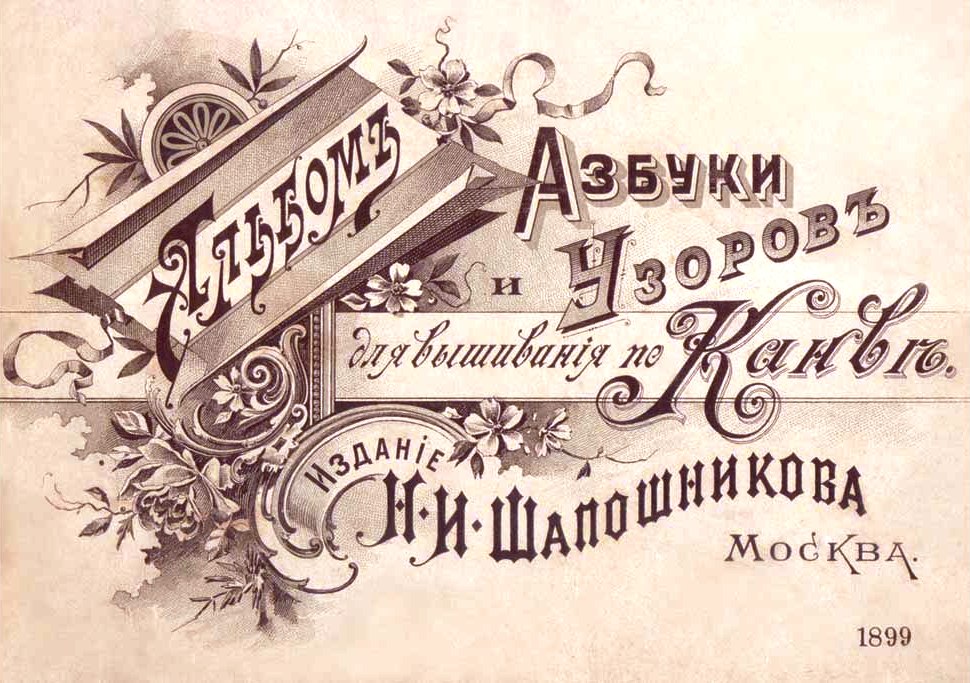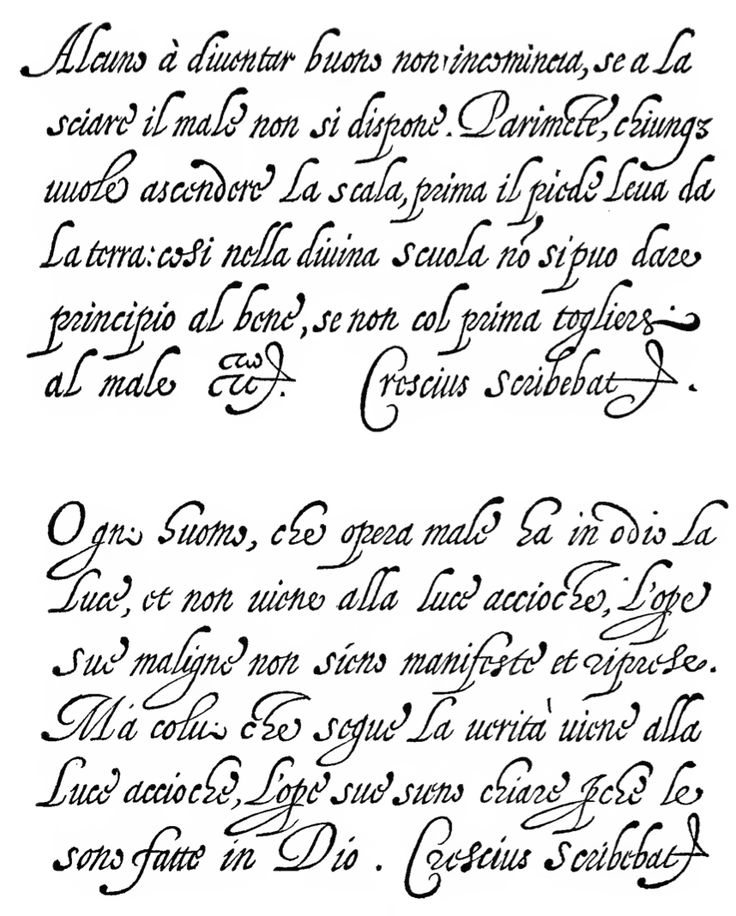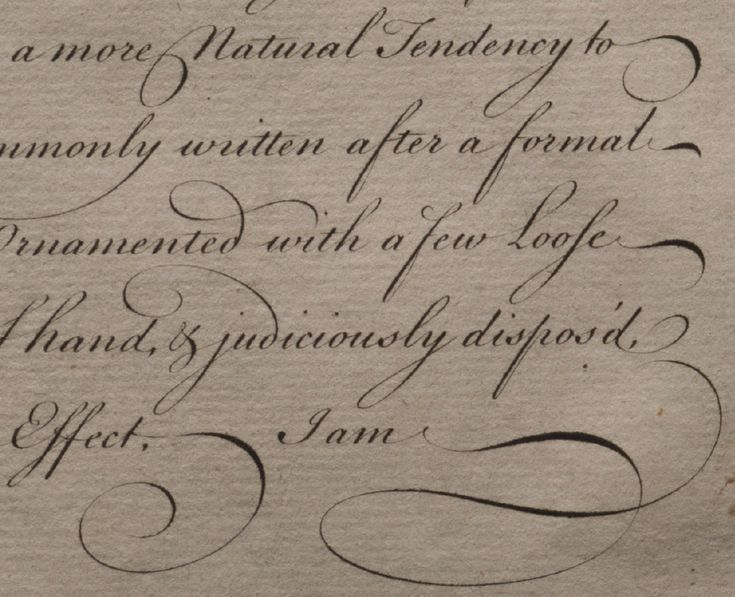
Лучшие шрифты для вашего сайта
Дизайн сайта проходит в много этапов. Один из последних, но также очень важных вопросов — это выбор шрифтов для оформления ваших текстов. У вас уже есть готовый дизайн сайта, планируете его наполнение, есть ли у вас готовые тексты и описания (копия) и графический дизайн? Итак, самое время начать работать над типографикой и выбирать идеальный шрифт! Чтобы помочь вам в этом, мы подготовили для вас подборку лучших шрифтов из разных категорий. Познакомьтесь с самыми интересными, креативными шрифтами и используйте их по своему желанию при работе над своими проектами!
Шрифт и характер вашей отрасли
Типографика — важный элемент дизайна и коммуникации, который влияет на восприятие посетителями веб-сайта и бренда или человека, которому он принадлежит.
Залог успеха в том, что каждый элемент дизайна сайта согласован друг с другом и создает гармоничную композицию.
Правильно подобранный шрифт может многое рассказать о характере бренда, о том, что он хочет донести до получателей и какими ценностями он руководствуется. С другой стороны, неправильно подобранный шрифт может плохо отражать характер бренда, вводить пользователей в заблуждение и вызывать неадекватные ожидания. Вы можете сами убедиться, насколько важно обеспечить соответствие визуальной формы текста сообщению, потому что это так же важно, как и весь графический контент, видимый на веб-сайте.
Список лучших и самых интересных шрифтов
Несомненно, использование типографики требует определенного чувства стиля. Если вы боитесь, что у вас не получится, вы всегда можете выбрать универсальный шрифт, например Helvetica или Georgia. Вы также можете воспользоваться библиотеками шрифтов, такими как Google Fonts, которые предоставят вам доступ к огромному количеству бесплатных шрифтов.
Однако, если вы хотите выделить страницу или проект, который создаете (и, без сомнения, он будет иметь гораздо меньше шансов на успех), вам нужно сделать его более привлекательным. Это также подходящее время для некоторых экспериментов. В конце концов, выбор шрифта, имитирующего почерк, необычно, но он может стать бесценной визитной карточкой бренда.
Чтобы вам было проще выбрать единственный идеальный шрифт, мы подготовили список лучших и самых интересных предложений из более чем 51 категории.
Универсальные шрифты
Как распознать универсальные шрифты? Во-первых, они вам знакомы, потому что вы видите их каждый день. Вы, несомненно, знаете такие имена, как Helvetica или (по образцу ее и намного уродливее оригинала) Arial. Это универсальные шрифты!
Универсальные шрифты должны хорошо смотреться в любом размере (хотя, к сожалению, это не всегда стандарт), на любом портативном носителе (бумаге или экране компьютера) и в любом проекте. Типичная особенность универсальных шрифтов — большое количество диакритических знаков.
Однако нет никакой гарантии, что интересующий вас шрифт будет содержать нужные вам специальные символы! Поэтому всегда проверяйте, прежде чем выбирать шрифт со всеми поверхностями и поддерживает все основные языки!
Универсальные шрифты обычно используются на всех типах веб-сайтов и их содержимого, целевых страницах, статьях в блогах, в более длинных формах, таких как электронные книги или документы, интернет-магазины, приложения и многие другие. Если вы хотите, чтобы ваше общение было безопасным, приглушенным, а шрифт не выделялся, выберите один из них.
Lato
- Стиль: четкий, профессиональный, минималистичный, элегантный, классический.
Это простой универсальный шрифт, созданный польским дизайнером Лукашем Дзедзичем. Его можно успешно использовать в самых разных проектах. Lato — классический шрифт, который будет работать на большинстве веб-сайтов, целевых страниц, резюме или портфолио. Он подчеркивает профессиональный характер каждого проекта и очень легко читается.
Roboto
- Стиль: четкий, профессиональный, минималистичный, современный.
Roboto — это простой, но современный шрифт, разработанный Кристианом Робертсоном. Его приятно читать, и он хорошо смотрится как в тонкой версии, так и в жирном или черном цвете.
Calibri
- Стиль: легко читаемый, простой, современный, минималистский
Это очень минималистичный шрифт. Он не имеет лишних украшений и хранится в простой форме. Он хорошо подходит для небольших и более значимых текстов. Его можно комбинировать с более декоративным шрифтом в заголовках и заголовках.
Helvetica
- Стиль: простой, минималистичный
Это простой шрифт с сюжетом. Первоначально спроектированный в 1957 году Максом Мидингером. В настоящее время это один из самых популярных шрифтов, вдохновивший на создание многих новых шрифтов. Благодаря своей нейтральности он вписывается в любой контент.
Times New Romans
- Стиль: элегантный, классический, профессиональный
В этом шрифте очень хорошо сочетаются современность и история.
Впервые он был использован в 1932 году в лондонской газете Times и с тех пор ассоциируется с отраслью. Он идеально подходит для книг, газет или различных официальных документов. Однако не используйте его чрезмерно на веб-страницах, поскольку он немного устарел и может быть нечитаемым на экранах. Исключением могут быть страницы новостных сервисов типа «Нью-Йорк Таймс».
Например, сейчас вы читаете ← этот ⇅ текст →, набранный шрифтом Робóто. О нем пойдет речь дальше, но уже сейчас вы можете отметить для себя какие-то интересные характеристики в его рисунке.
Пример использования гарнитуры Panetteria студии «Леттерхэд».
Проблема в Узбекистане
Основная проблема типографики в Узбекистане — отсутствие
конкуренции в бизнесе.
Ощущается явный перевес возможностей отдельных финансовых групп, которые могут себе позволить хороших специалистов. Их продукция в большей степени отвечает современным требованиям качества дизайна.